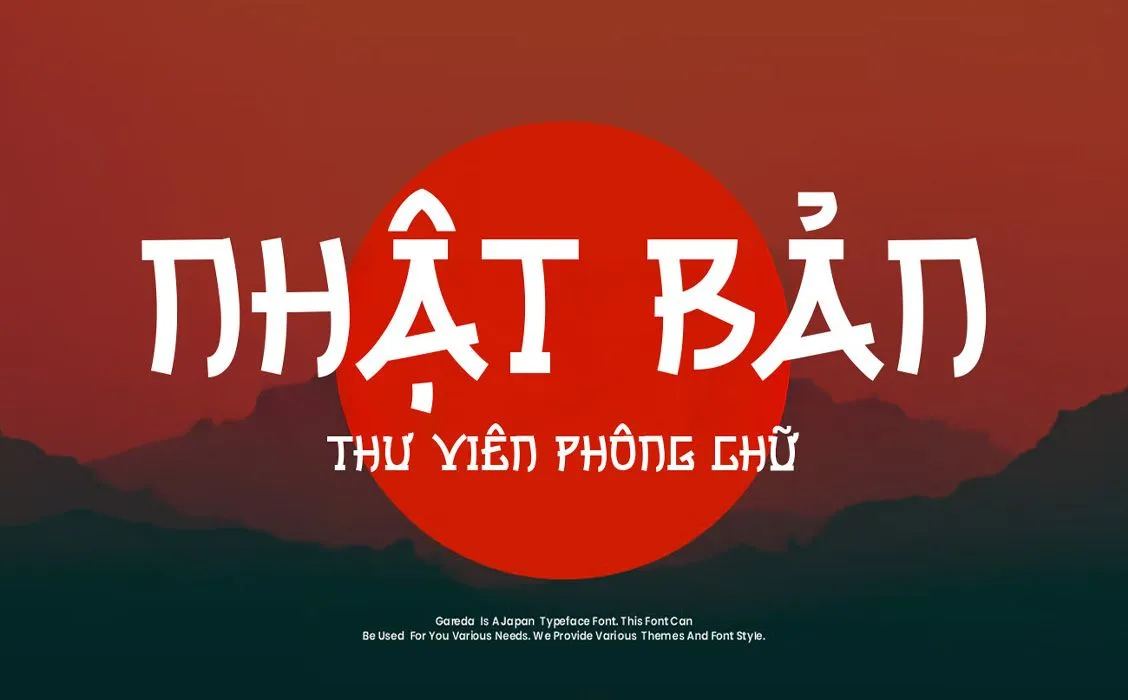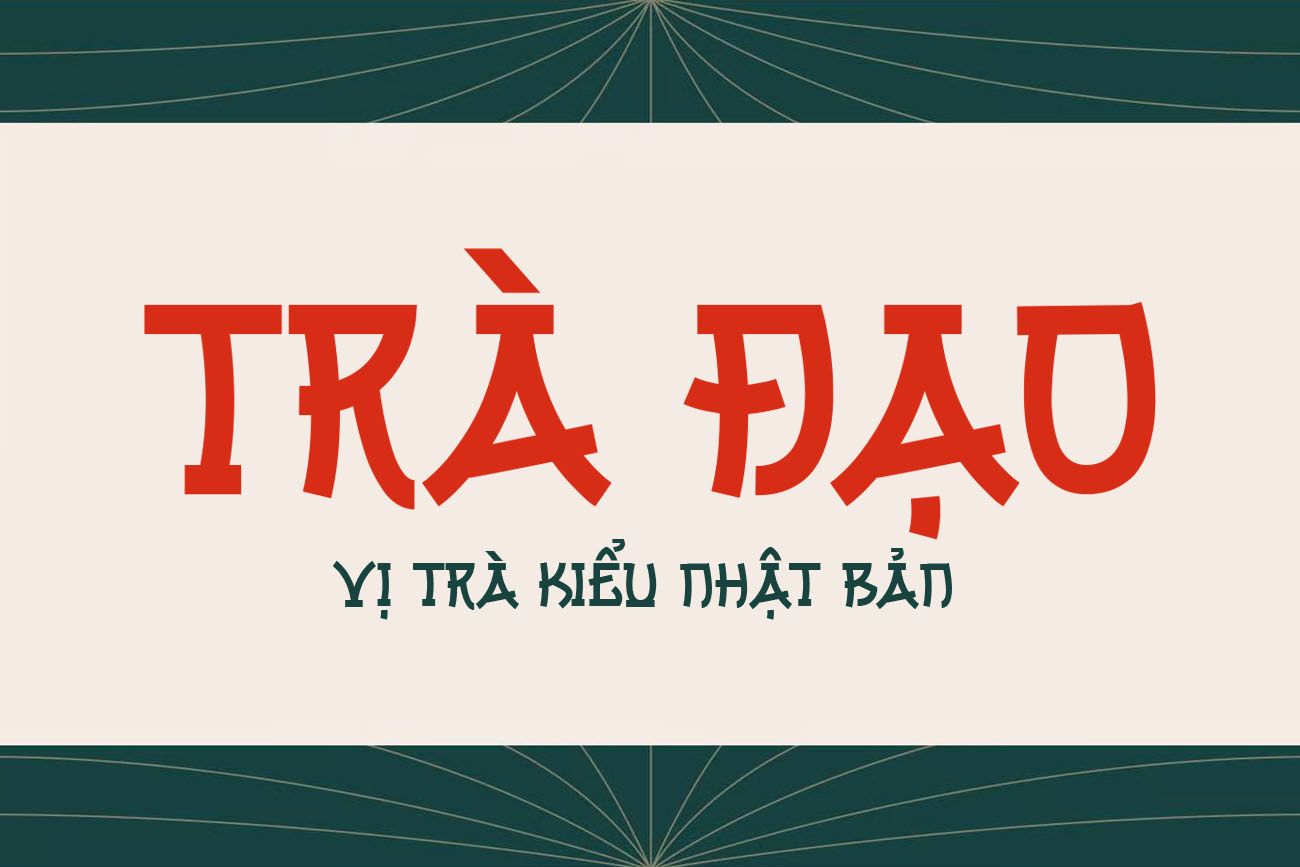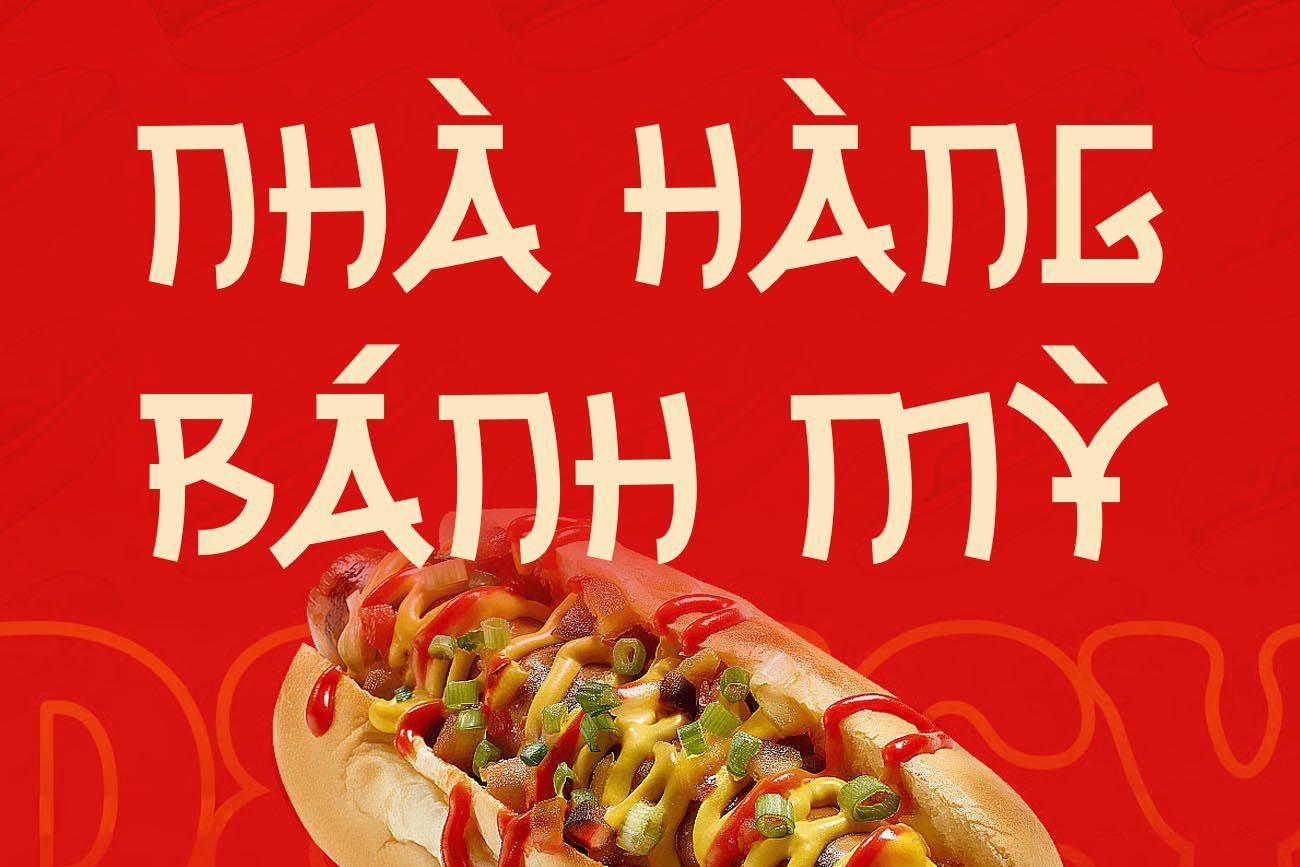
Mang linh hồn của xứ sở hoa anh đào vào từng nét vẽ, TH Gareda Việt hóa là một phông chữ Display đầy mạnh mẽ, tái hiện hoàn hảo vẻ đẹp của thư pháp Nhật Bản truyền thống. Những nhát cắt sắc lẹm, dứt khoát kết hợp cùng cấu trúc chữ mô phỏng phong cách chữ Hán giúp tạo nên một diện mạo độc bản, vừa hiện đại lại vừa đậm chất kiếm sĩ.
Bản Việt hóa của TH Gareda đã được xử lý kỳ công, đảm bảo các dấu tiếng Việt hòa quyện tự nhiên với tinh thần "Zen" tối giản nhưng đầy uy lực. Đây chính là lựa chọn số một cho các dự án:
Thiết kế Poster Anime/Manga: Tạo hiệu ứng thị giác mạnh mẽ và kịch tính.
Menu nhà hàng Nhật Bản: Tôn vinh nét văn hóa ẩm thực tinh tế qua từng dòng chữ.
Logo Streetwear: Mang lại phong cách bụi bặm, cá tính và đậm chất Á Đông.
Với TH Gareda, mỗi thiết kế của bạn sẽ trở thành một thông điệp nghệ thuật đầy sức sống và đậm đà bản sắc phương Đông.